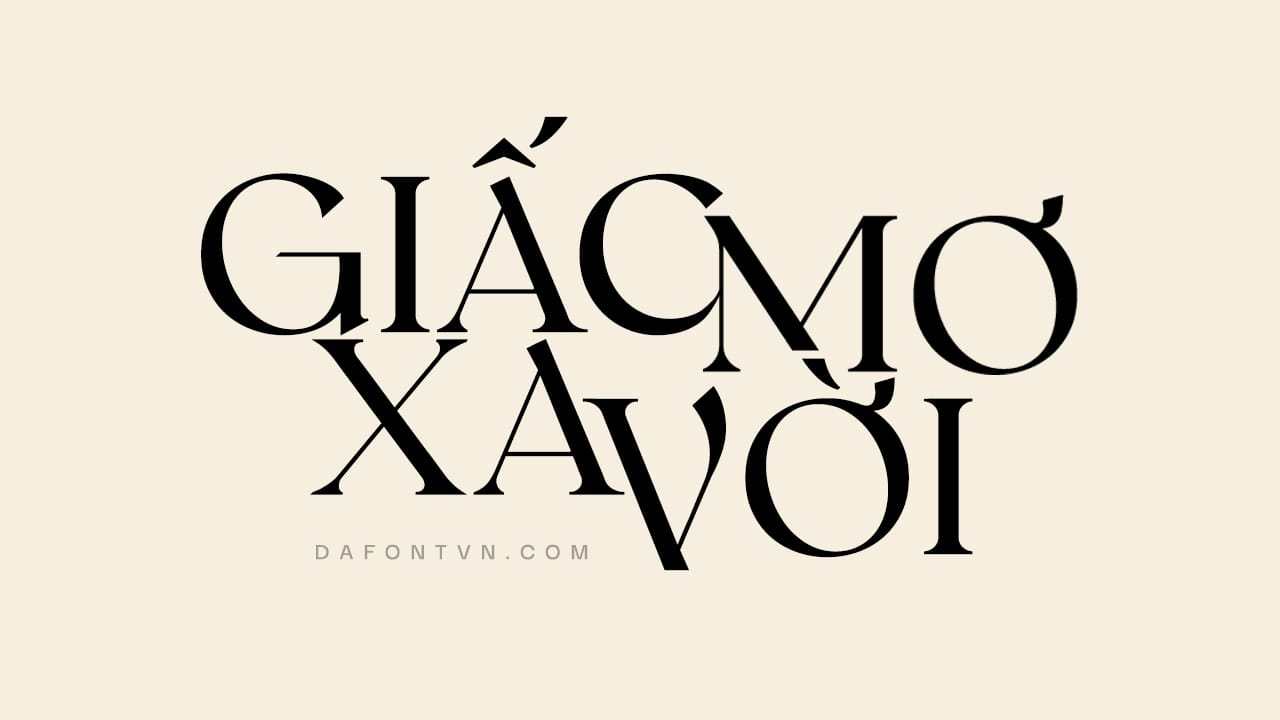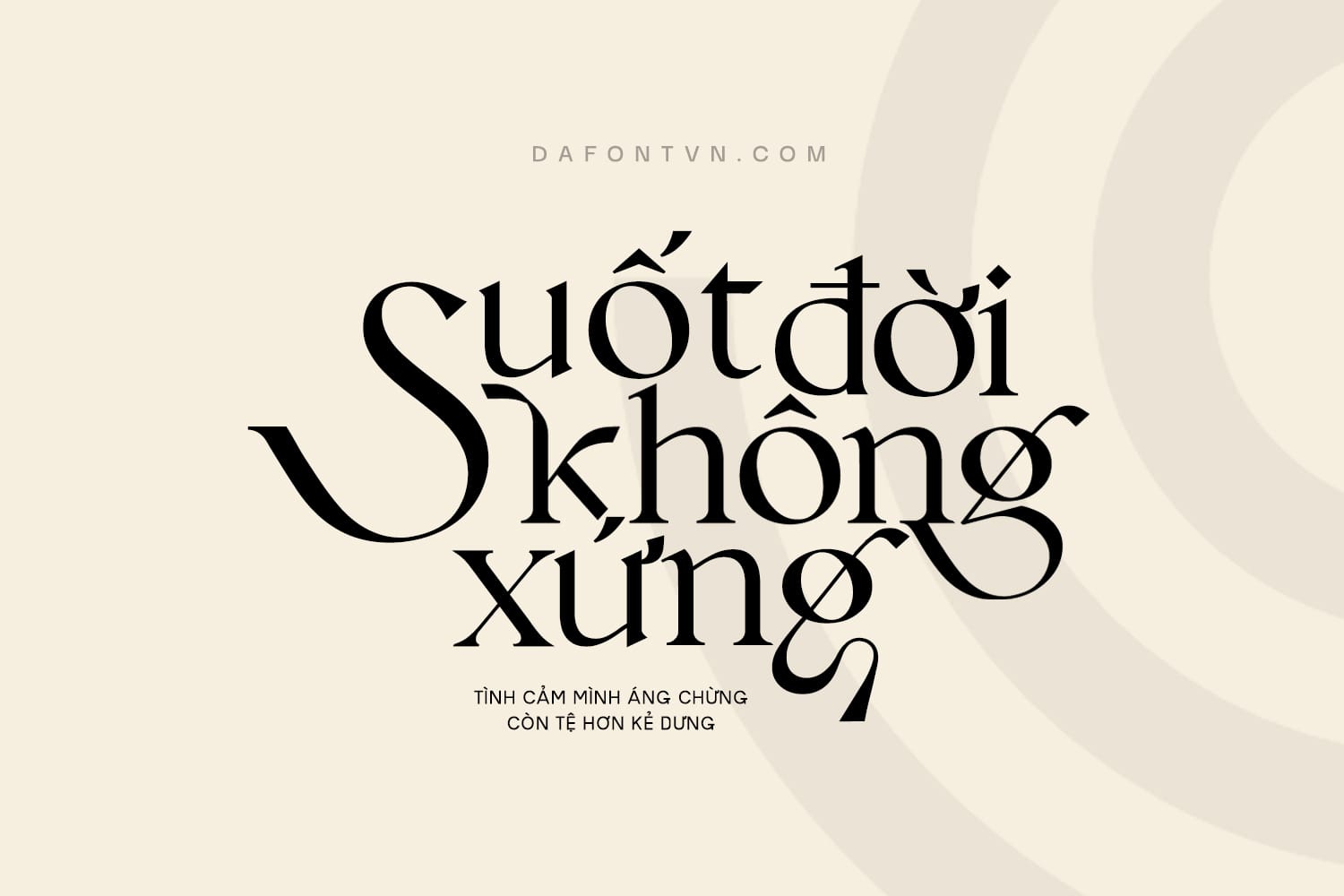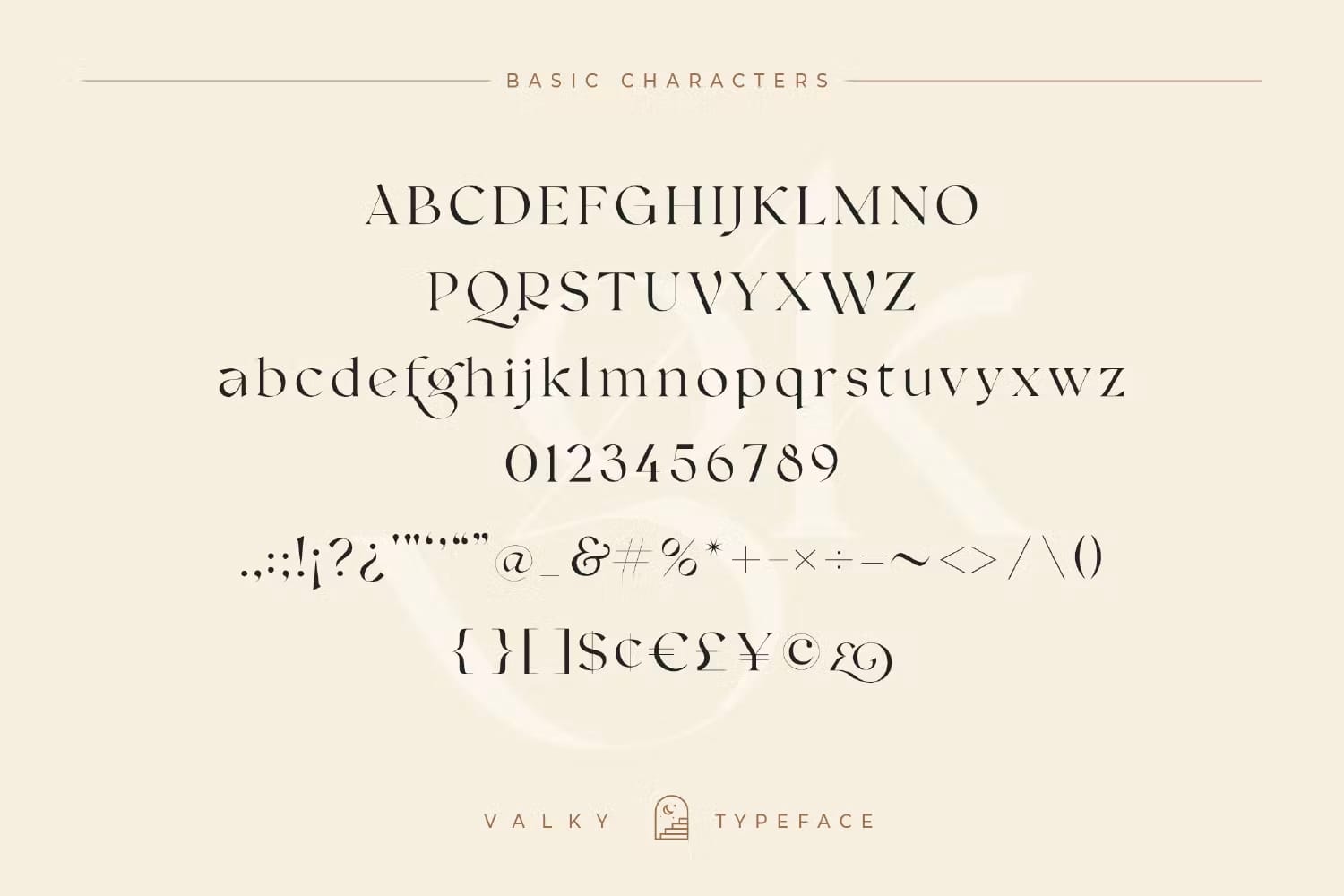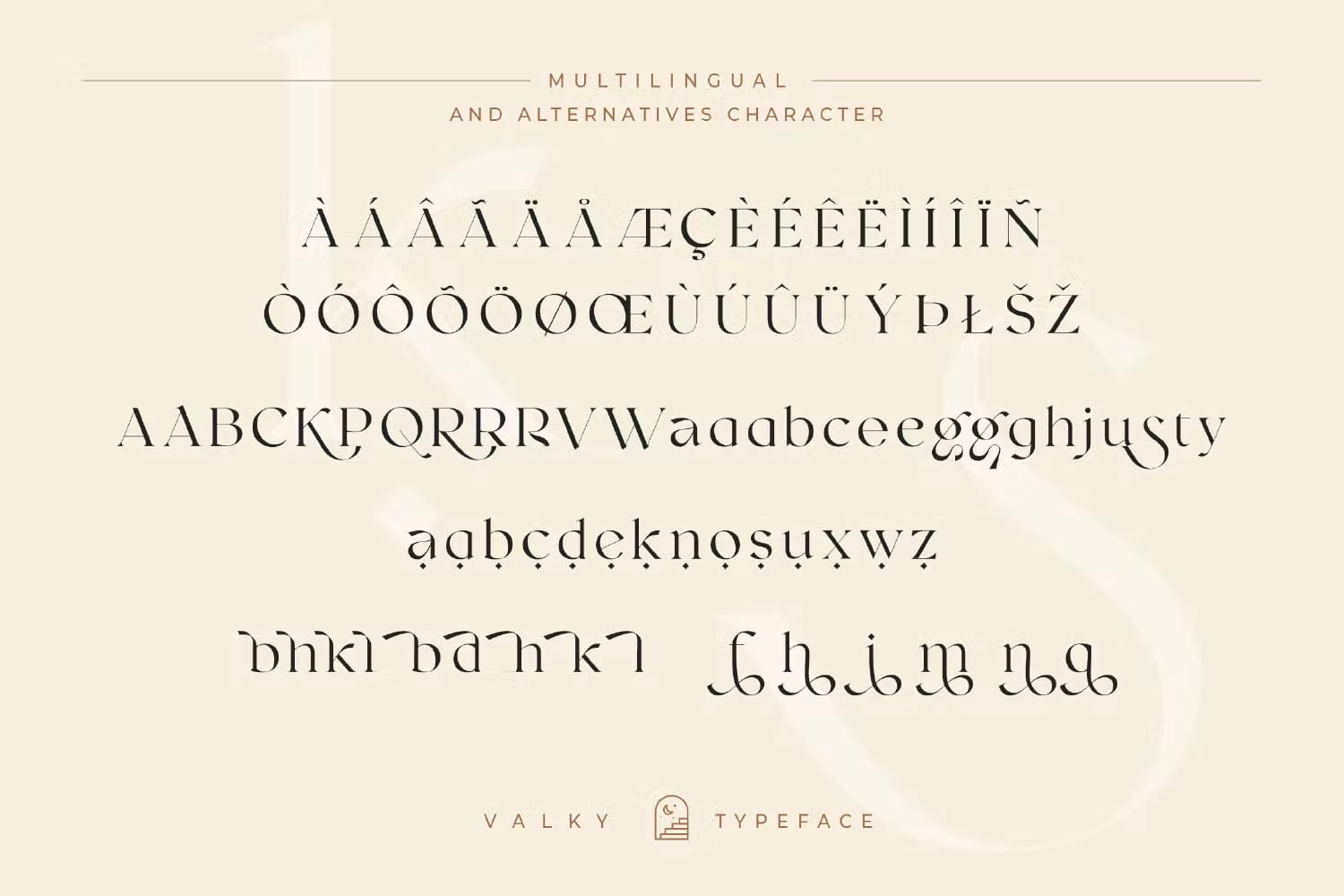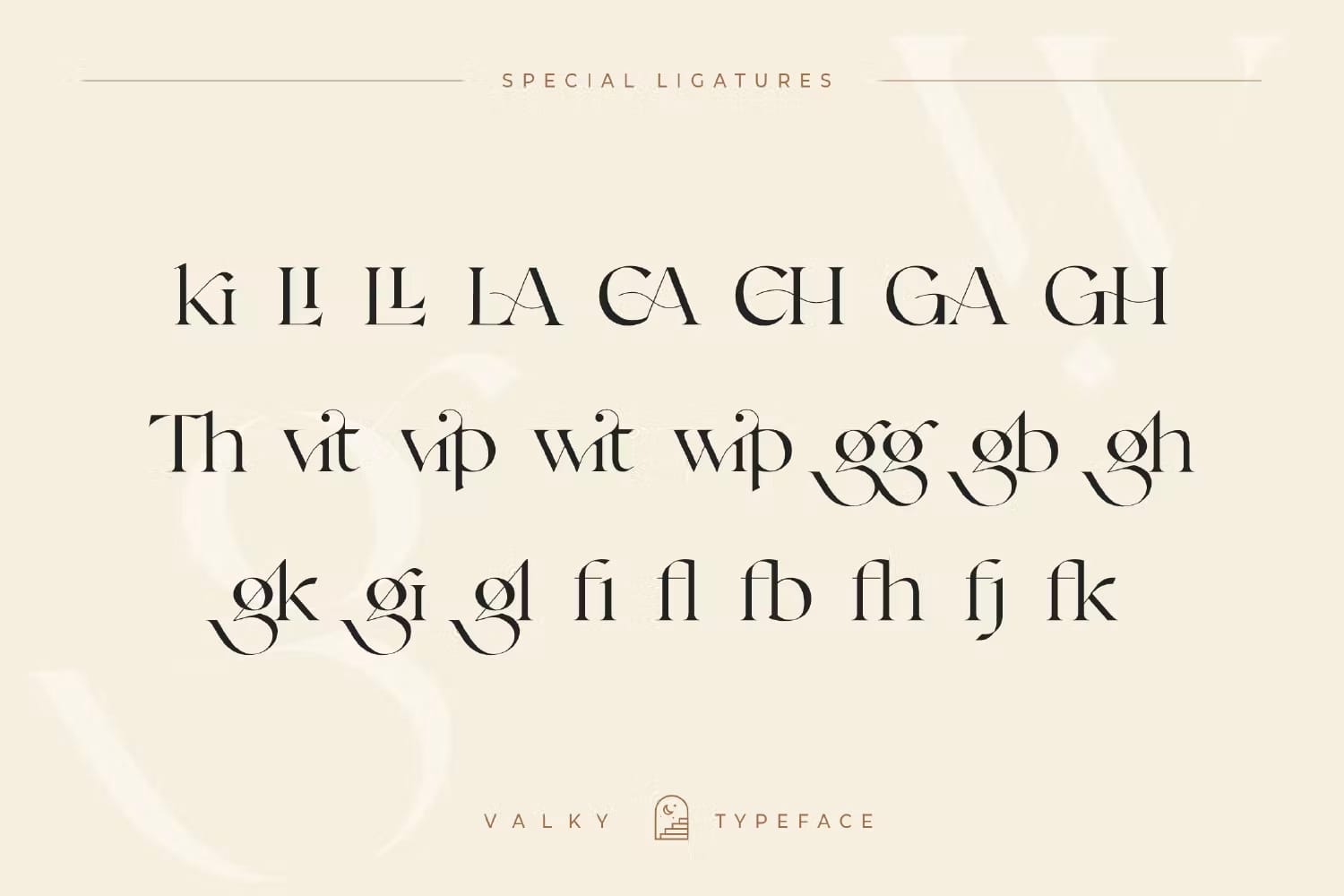
Font Valky Việt hóa v2 – Kiểu font hiện đại, cổ điển
Ở bài viết trước mình có share bộ font Valky việt hóa này rồi, đây là phiên bản việt hóa khác với các dấu có chút thay đổi so với bản trước và bao gồm đầy đủ 8 kiểu font việt hóa. Vì vậy các bạn thích bộ font nào thì có thể sử dụng nhé hoặc dùng cả 2 cũng được đỡ phải suy nghĩ.
Valky là kiểu chữ serif cổ điển nhưng cũng có 1 chút hiện đại lạ mắt với các chữ ghép đẹp, rất nhiều glyphs thay thế đặc biệt và hỗ trợ đa ngôn ngữ. Đây là một bộ phông chữ rất linh hoạt, hoạt động tuyệt vời ở các kích thước lớn và nhỏ.
Hoàn hảo cho các dự án biên tập, thiết kế logo, xây dựng thương hiệu, thời trang, quần áo, bao bì sản phẩm, tiêu đề tạp chí hoặc đơn giản là 1 kiểu font ấn tượng cho bất kỳ thiết kế nào.